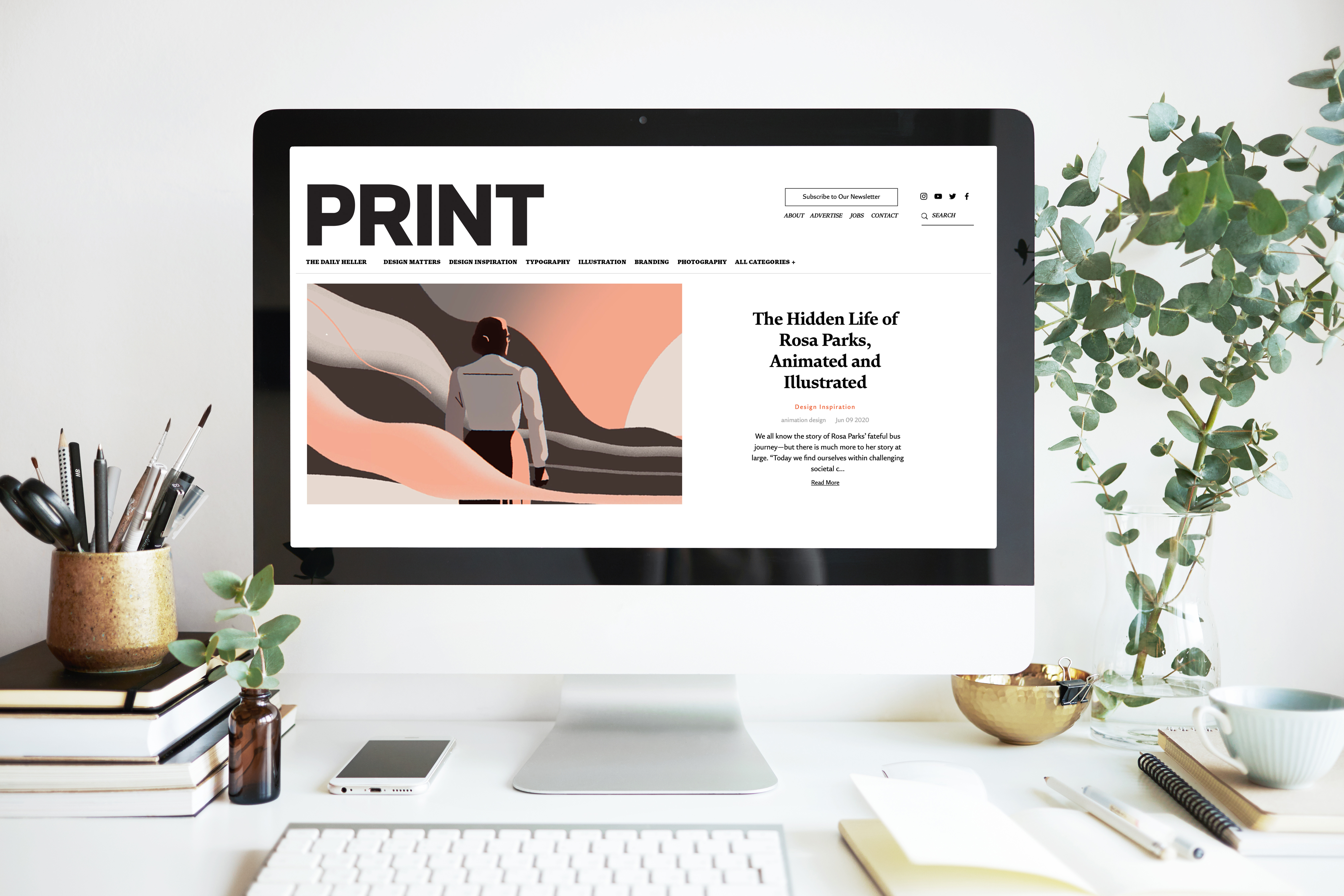
モリサワ 欧文スーパーファミリー「Role」が米国メディア『PRINT』のオフィシャルフォントに採用
株式会社モリサワの欧文スーパーファミリー「Role」が、米国デザインメディア『PRINT』のオフィシャルフォントに採用されました。「Role」がオフィシャルフォントとして採用されるのは初めてです。
『PRINT』は、1940年に創設された米国の著名なデザインメディアです。2019年に経営陣が変更されたことにより、編集チームも刷新されました。新編集チームは、AIGA(米国グラフィックアート協会)の名誉会長やNew York Timesで30年以上にわたりアートディレクターを努めた編集者など、米国デザイン業界を代表するデザイナー、ライター、編集者によって構成されています。
今回の再スタートに伴い、『PRINT』は新ウェブサイトを公開。「Role」は、タイトルや本文などウェブサイト内で広く採用されることになりました。アジアの実力フォントメーカのモリサワと、世界的書体デザイナーであるマシュー・カーター氏のコラボレーションで生まれた書体という斬新さや、デザインやウエイトの豊富さが評価されました。
「Role」について